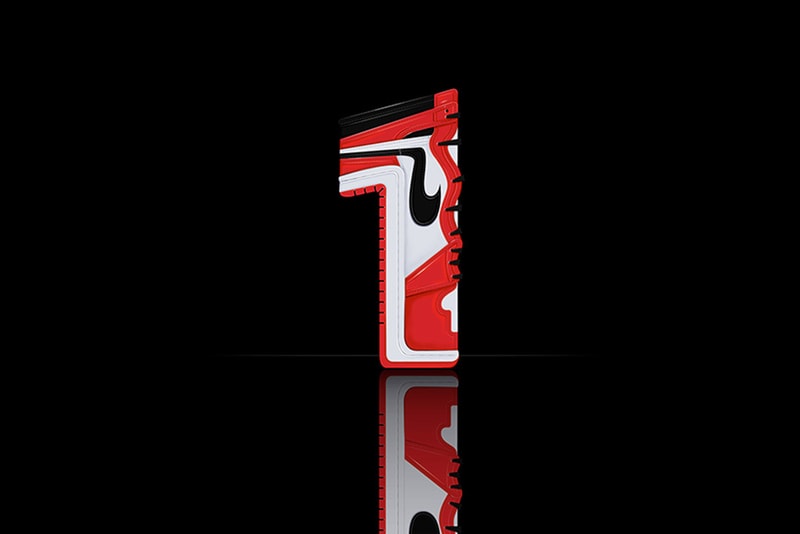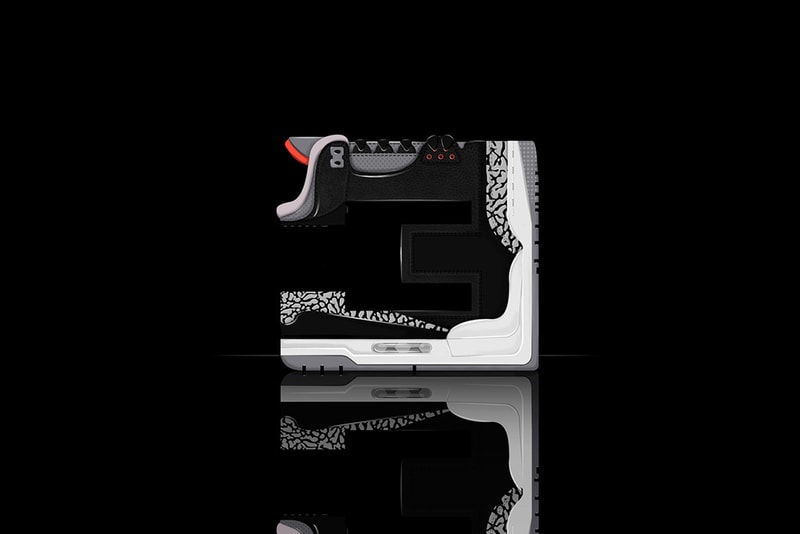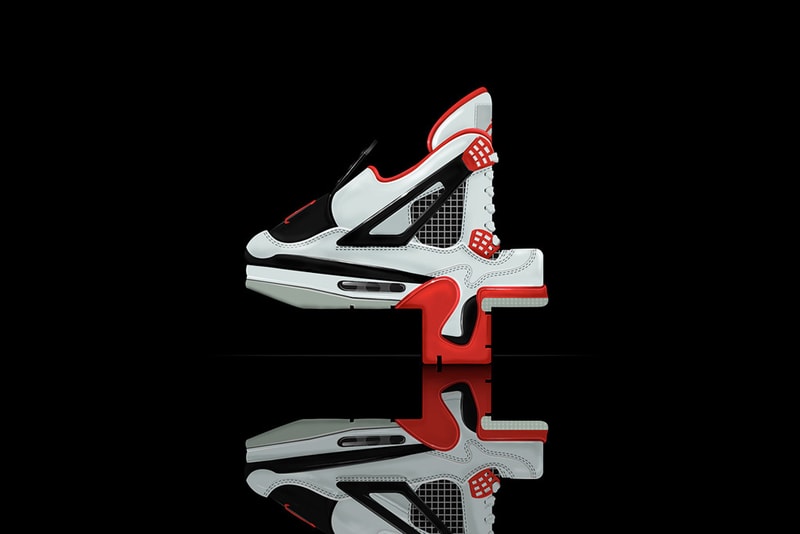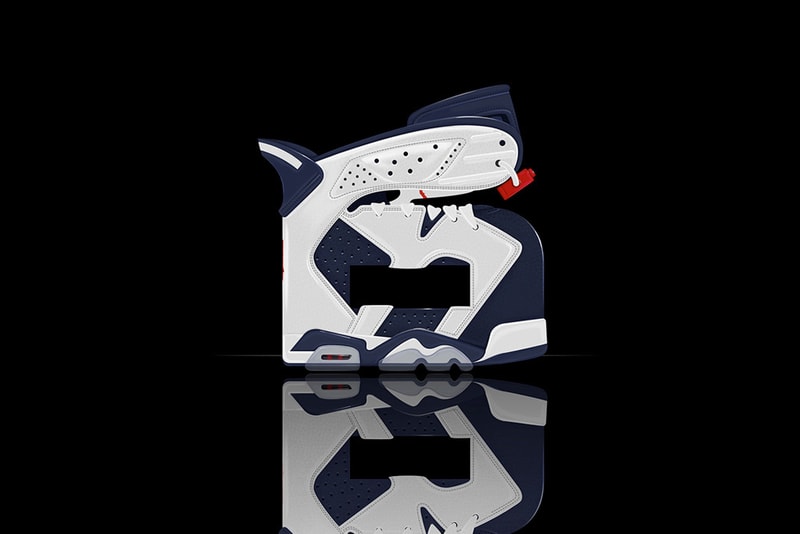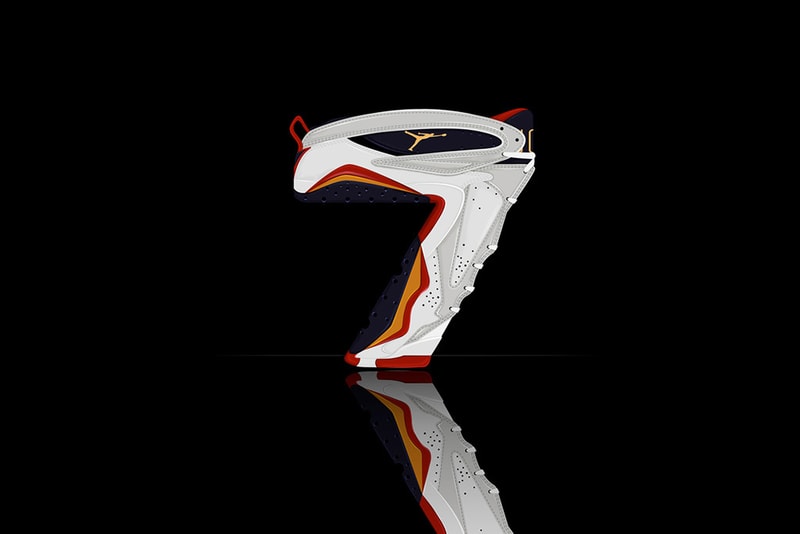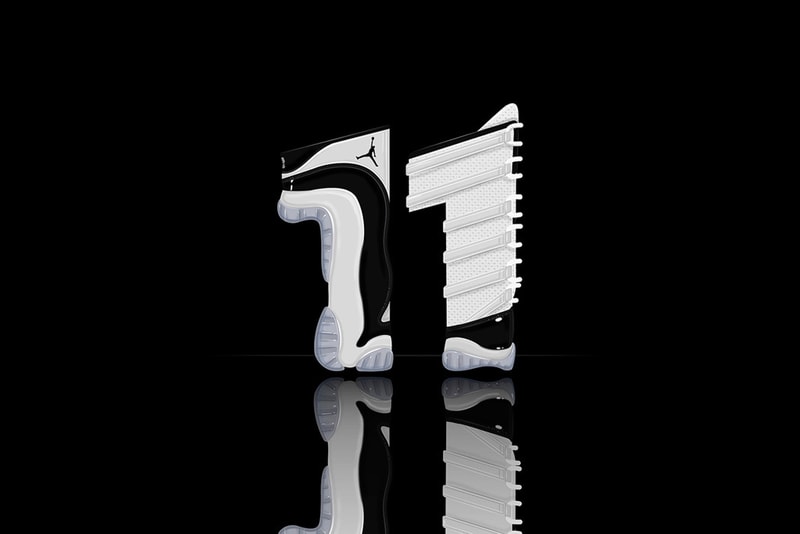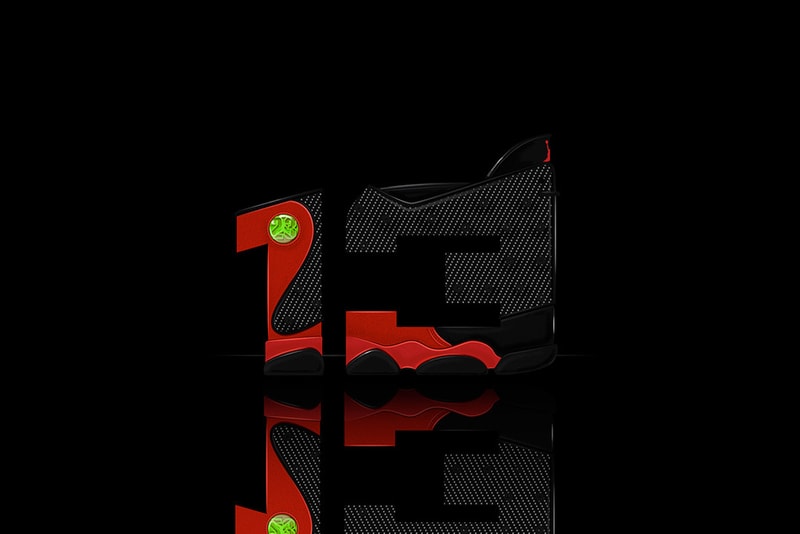
13th Collective 与 Will C. Smith 合作打造 Air Jordan 创意字体
来自俄勒冈的知名艺术家 Will C. Smith 以其充满创意的字体设计闻名,而本次他就与 13thCollective 合作,将 Air Jordan 球鞋系列
来自俄勒冈的知名艺术家 Will C. Smith 以其充满创意的字体设计闻名,而本次他就与 13thCollective 合作,将 Air Jordan 球鞋系列 进行解构,并以球鞋各部件组成其名称中的数字。设计师本人则称这项企划的灵感来源于他所钟爱的 Jordan 4 “Fire Man” 配色以及 Jordan Retro Card 乔丹收藏纸牌,首次发布的字体也以 Jordan 1 , 3 , 4 , 6 , 7 , 11 , 以及 13 这些经典款式的最热门配色构成。更多资讯可在 Behance 查看。